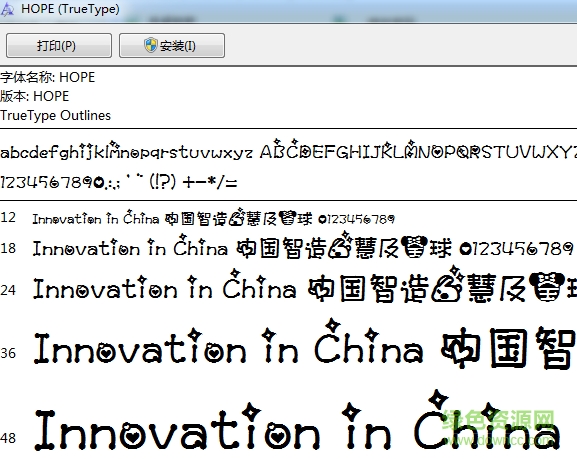
安靜的美女子字體是一款超好用的中文個(gè)性字體,字體非常具有少女氣息,具有獨(dú)特的個(gè)性,喜歡的用戶就趕快來(lái)綠色資源網(wǎng)免費(fèi)下載收藏吧!
安靜的美女子字體是一款極具個(gè)性的字體,該字體十分飄逸,彰顯了自己的個(gè)性,有喜歡的朋友可以來(lái)綠色資源網(wǎng)下載使用!